Въпрос към урок: Панелът Glyphs
Знакът за безкрайност не е ли математически символ и е без значение с какъв шрифт работим?
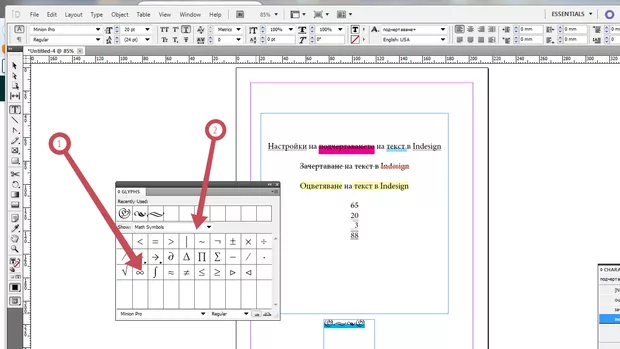
Ще го виждаш като знака "безкрайност" в повечето шрифтове, но пък ще го виждаш по различен начин - големина, изписване и т.н.